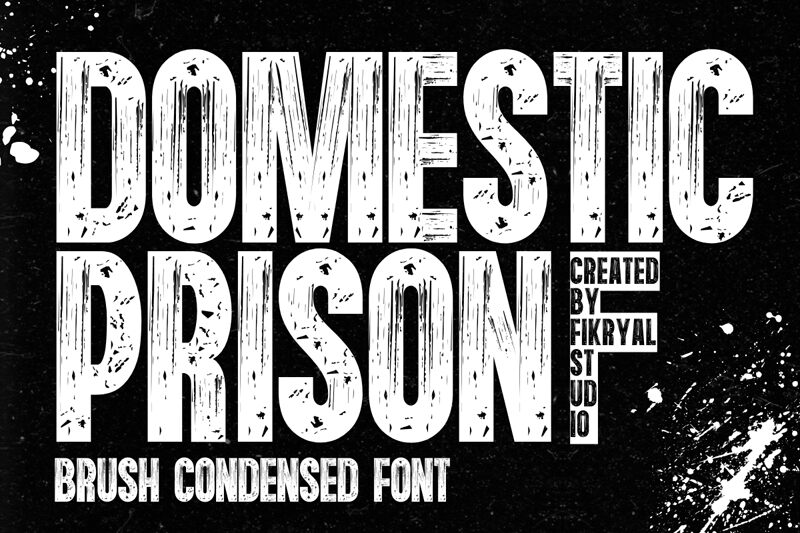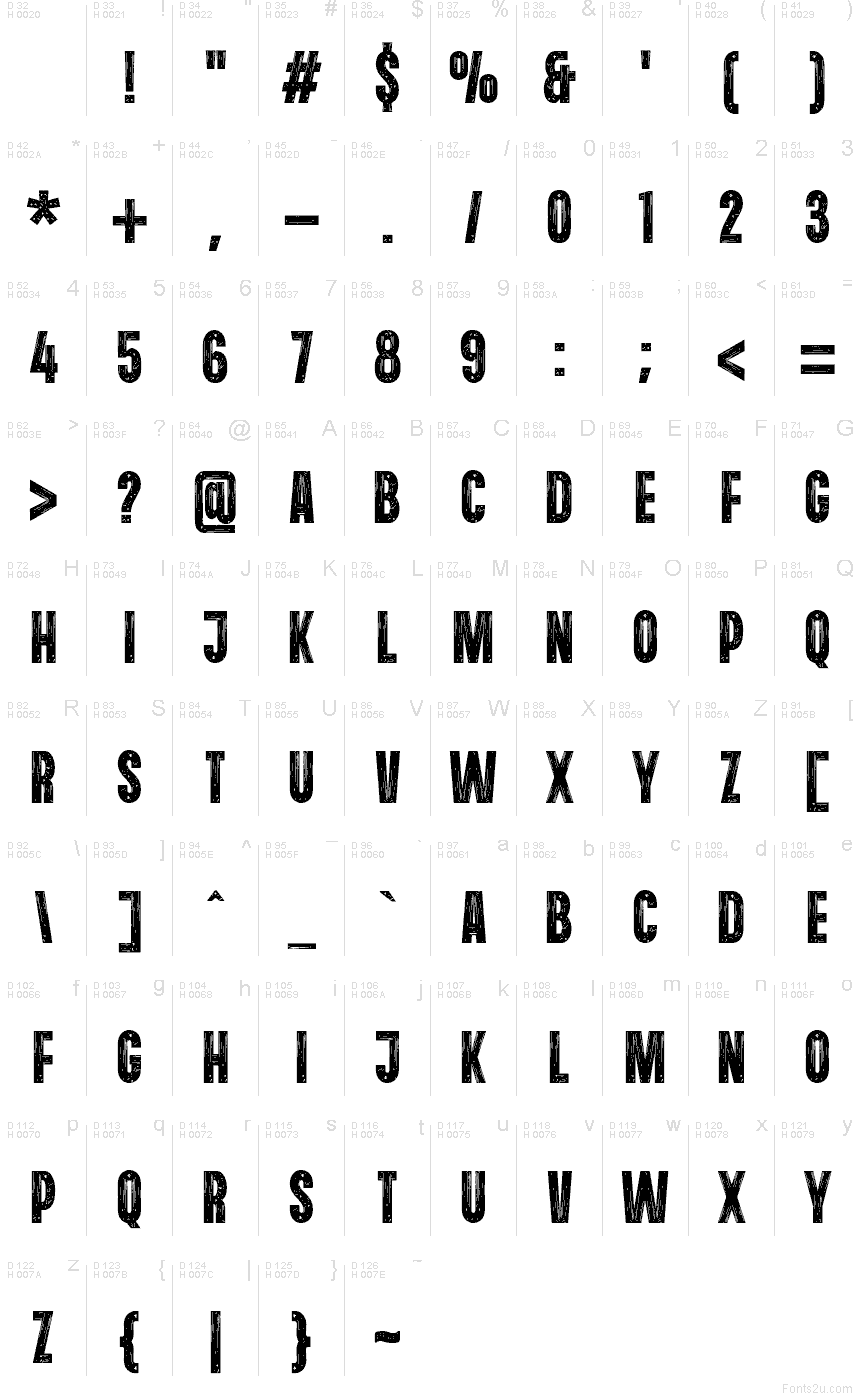
Il font Domestic Prison di Muhamad Fikry Nuralif (Fikryal Studio) colpisce come un avviso stampato: lettere maiuscole alte e condensate con graffi crudi e un inchiostro irregolare, come se fossero state trascinate su carta ruvida. La texture non è rifinita; è graffiata, consumata e rumorosa. È un font eroso gratuito che si legge velocemente anche quando sembra usurato.
Usa Domestic Prison su poster, copertine di album, grafiche streetwear, key art per videogiochi, volantini di protesta, titoli per thriller o miniature YouTube d'impatto per dare alla tua comunicazione una tensione immediata. Usalo in grande con un tracking generoso e abbinalo a un sans serif pulito per i dettagli: questo font gratuito grida, mentre l'altro mantiene la leggibilità.